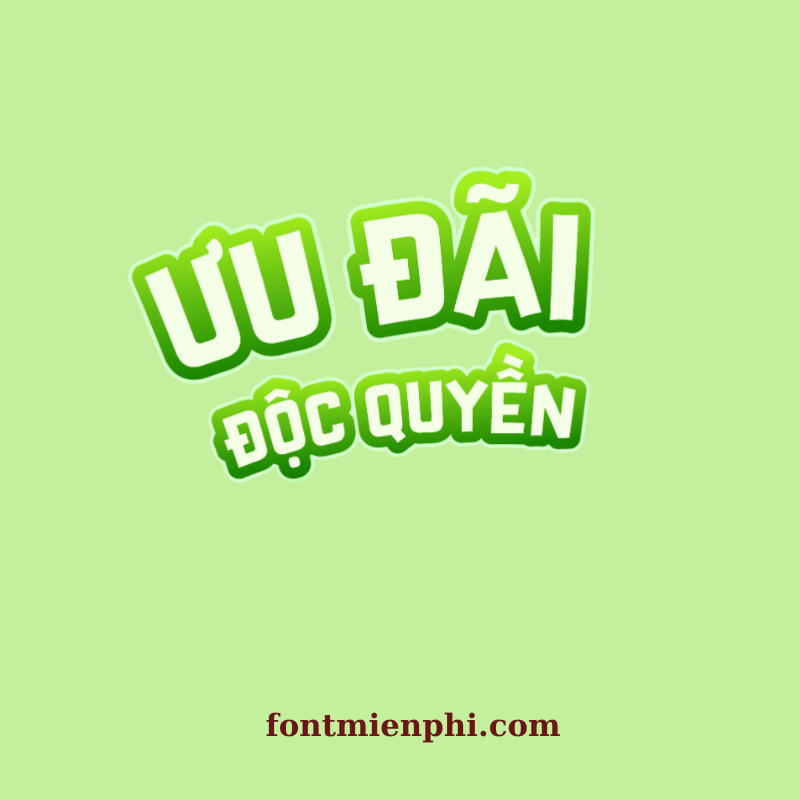
Font Việt hóa 1FTV VIP Crazy Sixties
Font Việt Hóa 1FTV VIP Crazy Sixties – Phong Cách Retro Độc Đáo
Font Việt hóa 1FTV VIP Crazy Sixties là bộ font chữ mang đậm phong cách retro những năm 1960, được thiết kế độc quyền với kiểu dáng sáng tạo, nét chữ uốn lượn mềm mại. Font hỗ trợ đầy đủ tiếng Việt, phù hợp cho thiết kế poster, bìa sách, logo, và các dự án nghệ thuật cần sự phá cách. Với đường nét bắt mắt, Crazy Sixties giúp tạo điểm nhấn ấn tượng cho mọi ấn phẩm.
• Phong cách retro độc đáo: Lấy cảm hứng từ thập niên 60, font chữ mang đến cảm giác hoài cổ nhưng vẫn hiện đại.
• Hỗ trợ tiếng Việt: Đầy đủ dấu, tương thích với mọi phần mềm thiết kế.
• Đa dạng ứng dụng: Dùng cho in ấn, quảng cáo, thời trang, âm nhạc, và nghệ thuật.
• Nét chữ nghệ thuật: Đường cong mềm mại, độ dày nét cân đối, dễ đọc nhưng vẫn sáng tạo.
Font Crazy Sixties phù hợp với:
• Thiết kế poster phim, sự kiện.
• Trình bày bìa tạp chí, album nhạc.
• Tạo logo thương hiệu cá tính.
• Thiết kế quảng cáo, banner website.